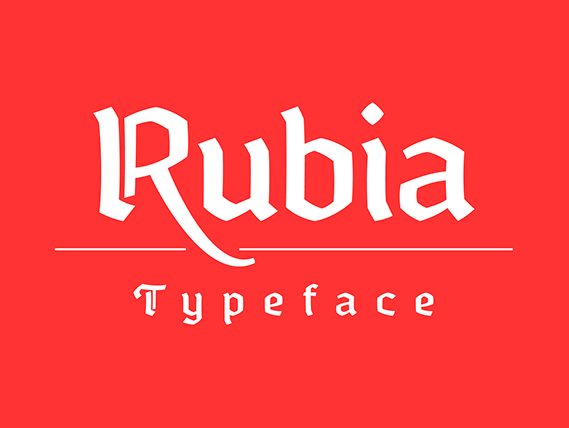
Rubia Typeface
A Rubia Typeface é uma elegante família de caracteres tipo display criada por Hamilton. Essa fonte oferece uma variedade impressionante de opções para criar mensagens impactantes e personalizadas. Se você está procurando um estilo icônico, a Rubia pode ser a solução perfeita, com suas formas arredondadas e traços elegantes que deixam um forte impacto visual em qualquer tipo de mídia. Ela é ideal para usar em elementos de marca ou design gráfico criativos, como logotipos e grafismos. Se você está procurando por um estilo similar a fontes gratuitas com uso pessoal disponíveis, você pode encontrar mais opções semelhantes no befonts. A Rubia é uma ótima escolha para designers que valorizam tanto o design de marcas quanto o impacto visual de suas criações.